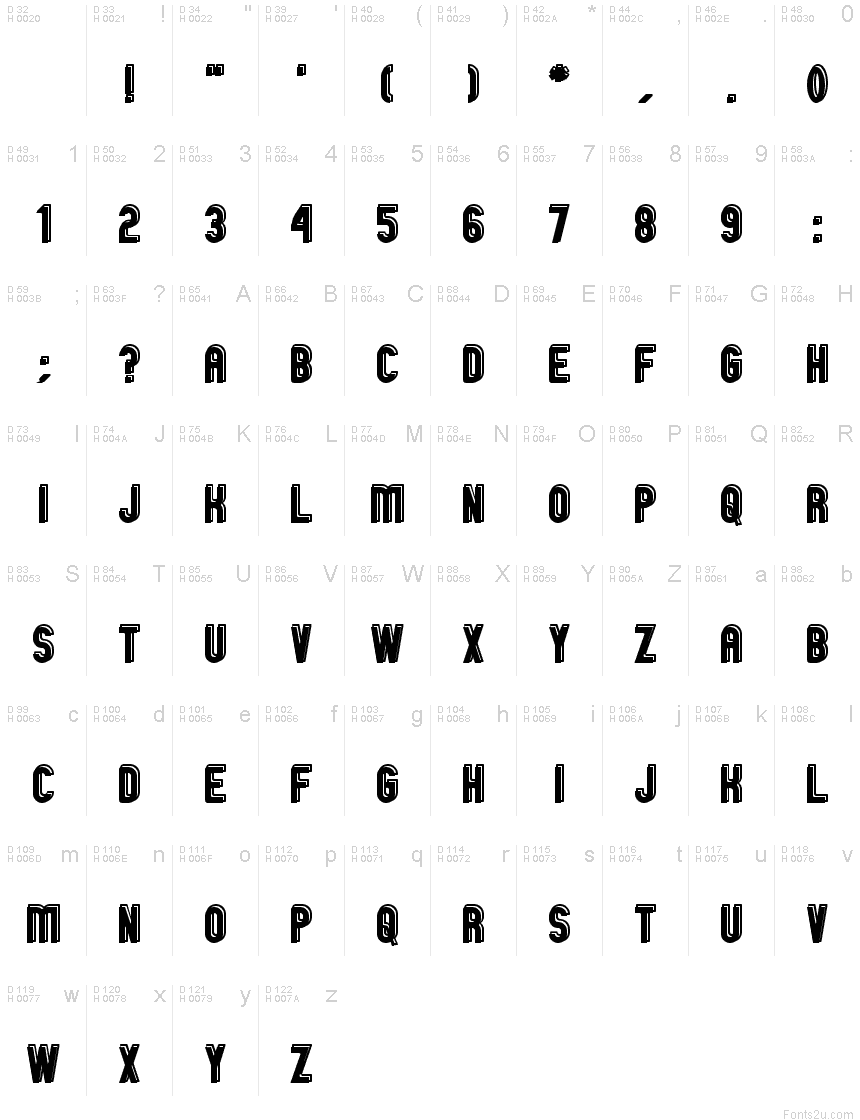
GM Exp Offset Outline od G.M. to bezpłatny, wyrazisty krój wyświetlaniowy z konturem, który natychmiast nadaje projektom plakatową energię. Wysokie, kompaktowe litery otoczone grubymi, przesuniętymi konturami tworzą wbudowany efekt cienia, dzięki czemu słowa sprawiają wrażenie wybitych, ułożonych w stos i lekko trójwymiarowych. Rytm pociągnięć jest ciasny i dynamiczny, co nadaje nagłówkom mocny, niemal industrialny charakter, nie sprawiając przy tym wrażenia sztywności.
Używając GM Exp Offset Outline, możesz przyciągać wzrok na plakatach eventowych, grafikach sportowych, tytułach gier retro, odważnych logotypach, szyldach i gadżetach, które muszą być czytelne z daleka. Ten bezpłatny font najlepiej prezentuje się w dużym rozmiarze, pozwalając, by przesunięty kontur wykonał całą wizualną pracę; w tekście głównym połącz go z czystym, dyskretnym krojem bezszeryfowym, aby skupić uwagę na jego masywnych, rzeźbiarskich formach.
GM Exp Offset Outline